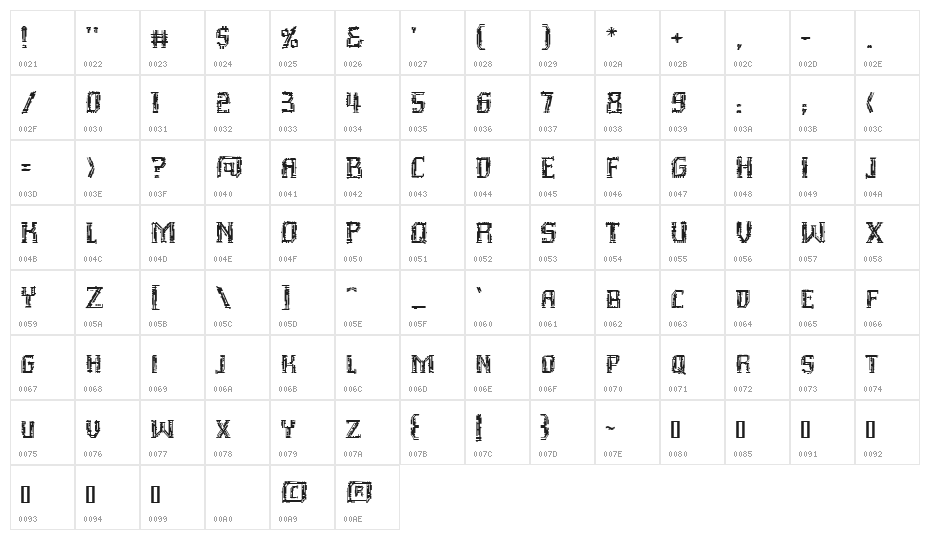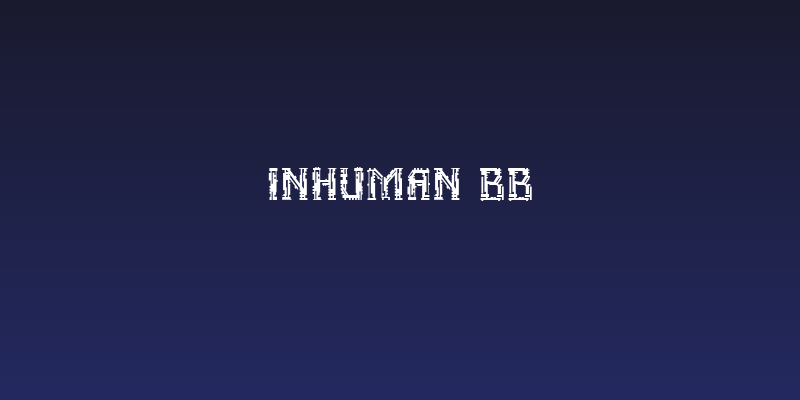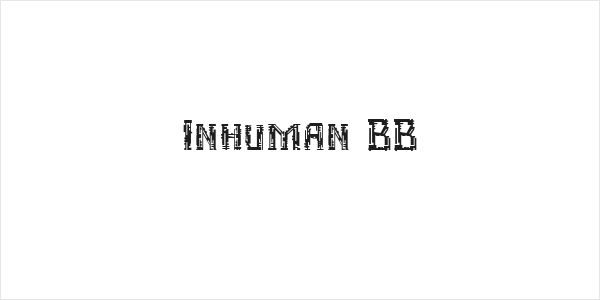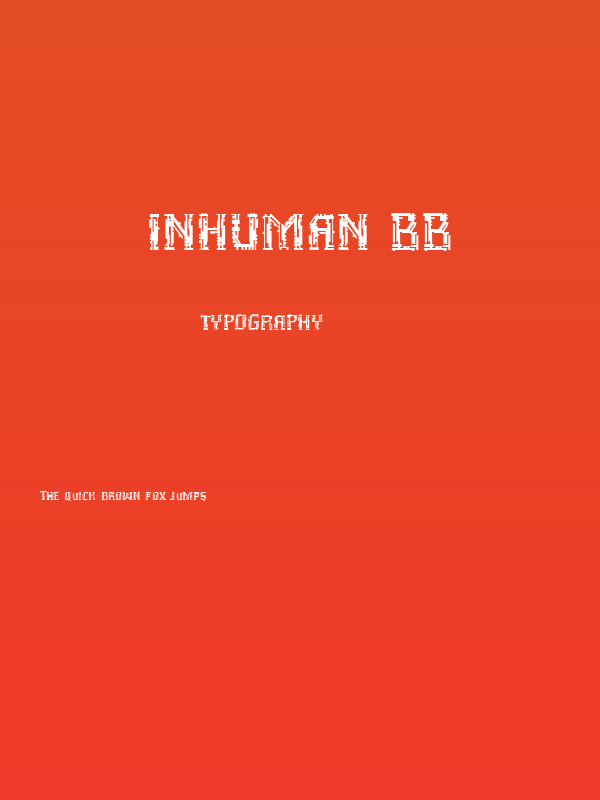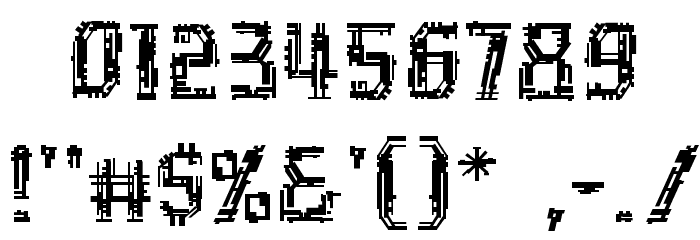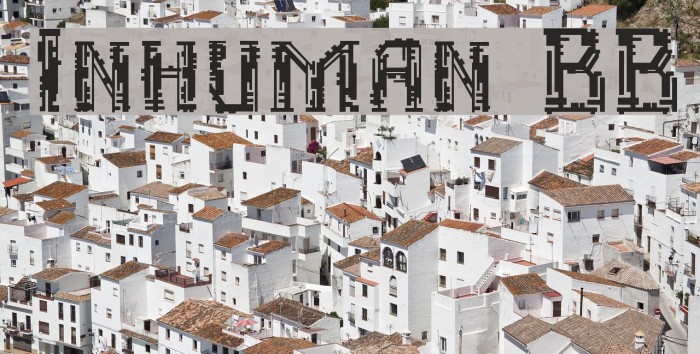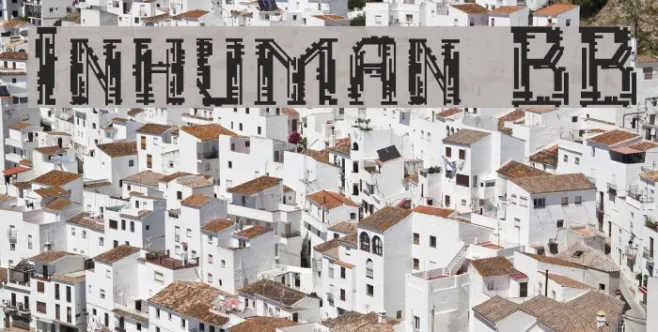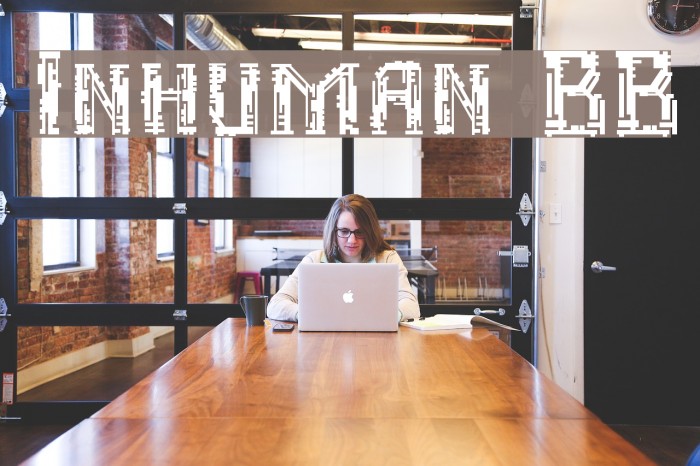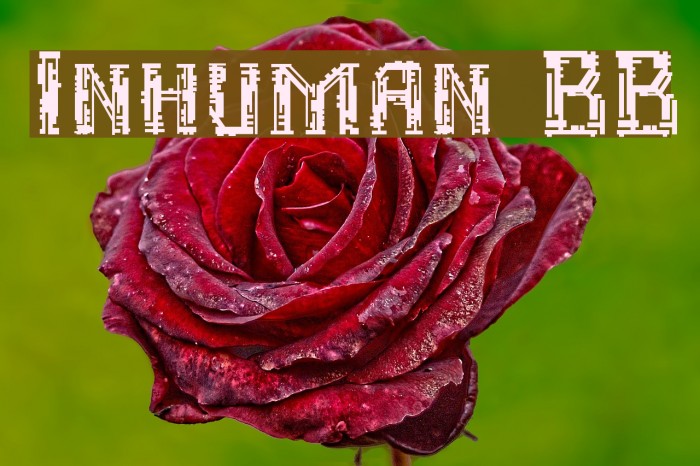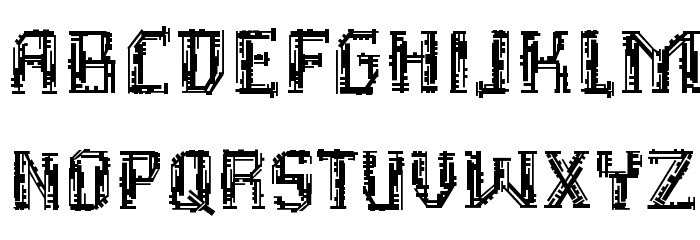
Inhuman BB Font
| Stile generale | Modern, Futuristic |
| Progetti proposti | Ideal for tech-themed posters, video game graphics, sci-fi book covers, and digital art projects. |